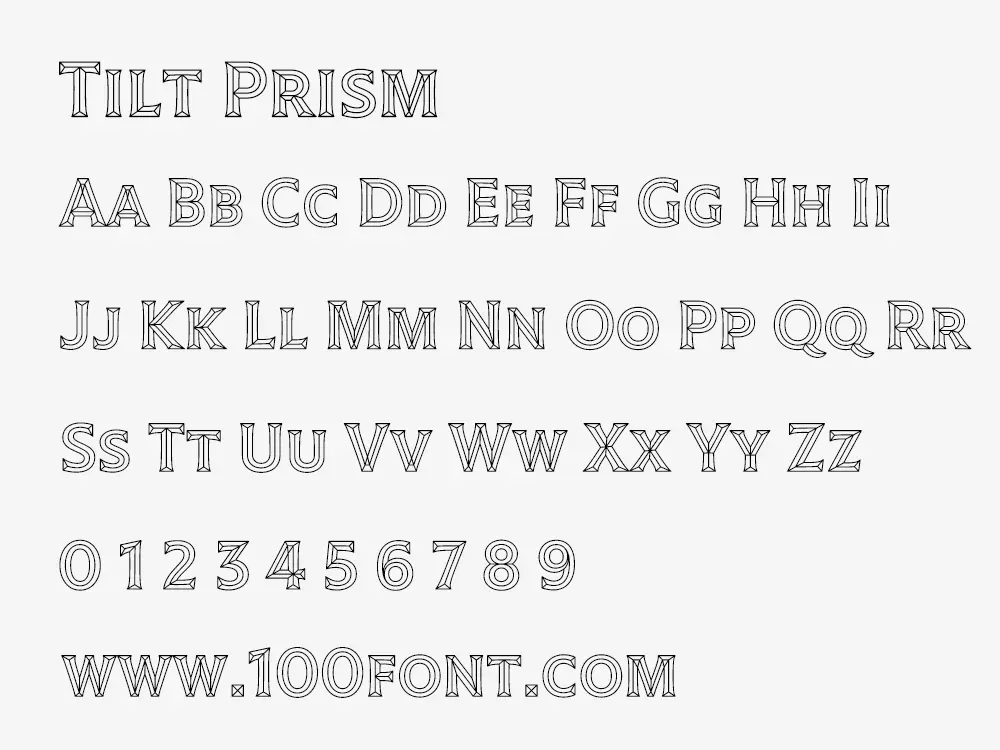
Tilt字體系列的靈感來自店面標識中的立體字體,由Andy Clymer設計。它由三種相關的可變字體樣式組成,您可能會在商店櫥窗中找到
● Tilt Neon模仿霓虹燈燈管的結構,
● 傾斜稜鏡是基於稜柱形刻字,鑄造或切割在一個材料,
● Tilt Warp類似於脫皮的乙烯基貼紙。
這三種字體都是基於一個標識畫家的幾何無襯線字體的相同字母模型,類似於Futura或Avant Garde字體,但有一些你可能會在用畫筆繪製字母時看到的細節。
這三種樣式被設計和構建為可變字體。這些字體允許用戶使用“旋轉X軸”和“旋轉Y軸”來旋轉字形的方向,而不是使用您期望找到的“重量”和“寬度”等變化軸。旋轉限制在±45°,這樣字體就不會旋轉超過可讀範圍。
Tilt is a family of type inspired by the dimensional lettering found in storefront signage, designed by Andy Clymer. It’s comprised of three related variable font styles that you might find in a shop window —
● Tilt Neon mimics the construction of neon tube lettering,
● Tilt Prism is based on prismatic lettering, cast or cut in a material,
● Tilt Warp resembles peeling vinyl stickers.
All three are based around the same letter model of a sign painter’s geometric sans serif, similar to the typefaces Futura or Avant Garde, but with the kinds of details you might expect to see when the letter is built up with a brush.
The three styles are designed and built as variable fonts. Instead of using variation axes that you would expect to find, such as “Weight” and “Width”, these typefaces allow users to rotate the orientation of their glyphs with “Rotation in X” and “Rotation in Y” axes. The rotation is limited to ±45° so that the letterforms never rotate past a readable range.